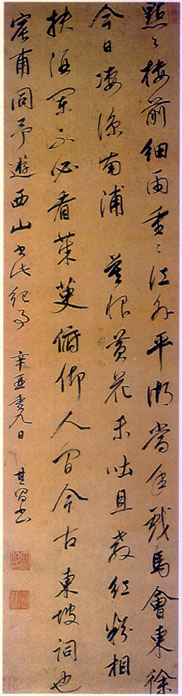
董其昌
董其昌简介
字玄宰,号思白,又号香光居士,松江华亭( 今上海松江县)人,官至南京礼部尚书,谥文敏。世称“董香光”、“董文敏”、“董华亭”,在明末以书画名重海内。
董其昌学书道路是十分艰难的,起因是在考试时书法不好,遂发愤用功自成名家。这在他的《画禅室随笔》有所记述,其中还自述学书经过:“初师颜平原《多宝塔》,又改学虞永兴,以为唐书不如晋魏,遂仿《黄庭经》及钟元常《宣示表》、《力命表》、《还示帖》、《舍丙帖》,凡三年,自谓逼古,…比游嘉兴,得尽睹项子京家藏真迹,又见右军《官奴帖》于金陵,方悟从前妄自标评。”由此可见,他对于古代名家墨迹是认真临摹的,在用笔用墨和结体布局方面,能融会贯通各家之长。以古为师,以古为法,他的书法成就一方面得力于自己刻苦勤奋,善于深刻地悟通、反省,另一方面也不能忽视其与大收藏家项元汴的交往,得以饱览许多书画真迹。书法至董其昌,可以说是集古法之大成,“ 六体”和“八法”在他手下无所不精,在当时已“名闻外国,尺素短札,流布人间,争购宝之。”(《明史·文苑传》)。董其昌在仕途上的通达,不是明代前几位书家所能比拟的。到了清代,康熙又倍加推崇、偏爱,甚而亲临手摹董书,常列于座右,晨夕观赏。清代著名书家王文治《论书绝句》曾赞曰:“书家神品董华亭,楮墨空元透性灵。 除却平原俱避席,同时何必说张邢。”一时士子皆学董其昌的妍美、软媚,清初的书坛为董其昌笼罩,书风日下,实在是书坛的悲哀。对董其昌的批评者也很多,包世臣、康有为最为激烈。康有为《广艺舟双楫》云:“香光虽负盛名,然如休粮道士,神气寒俭。若遇大将军整军厉武,壁垒摩天,旌旗变色者,必裹足不敢下山矣。”
他的书法以行草书造诣最高,行书以“二王”为宗,又得力于颜真卿、米芾、杨凝式诸家,赵孟俯的书风也或多或少的影响到他的创作。草书植根于颜真卿《争座位》和《祭侄稿》,并有怀素的圆劲和米芾的跌宕。用笔精到,能始终保持正锋,作品中很少有偃笔、拙滞之笔;用墨也非常讲究,枯湿浓淡,尽得其妙;风格萧散自然,古雅平和,或与他终日性情和易,参悟禅理有关。许多作品行中带草,左图这幅作品用笔有颜真卿率真之意,体势有米芾的侧欹,而布局得杨凝式的闲适舒朗,神采风韵似赵孟俯,轻捷自如而风华自足。董其昌对自己的楷书,特别是小楷也相当自负。
董其昌学识渊博,精通禅理,是一位集大成的书画家,在中国美术史上具有一定的地位,其《画禅室随笔》是研究中国艺术史的一部极其重要的著作。